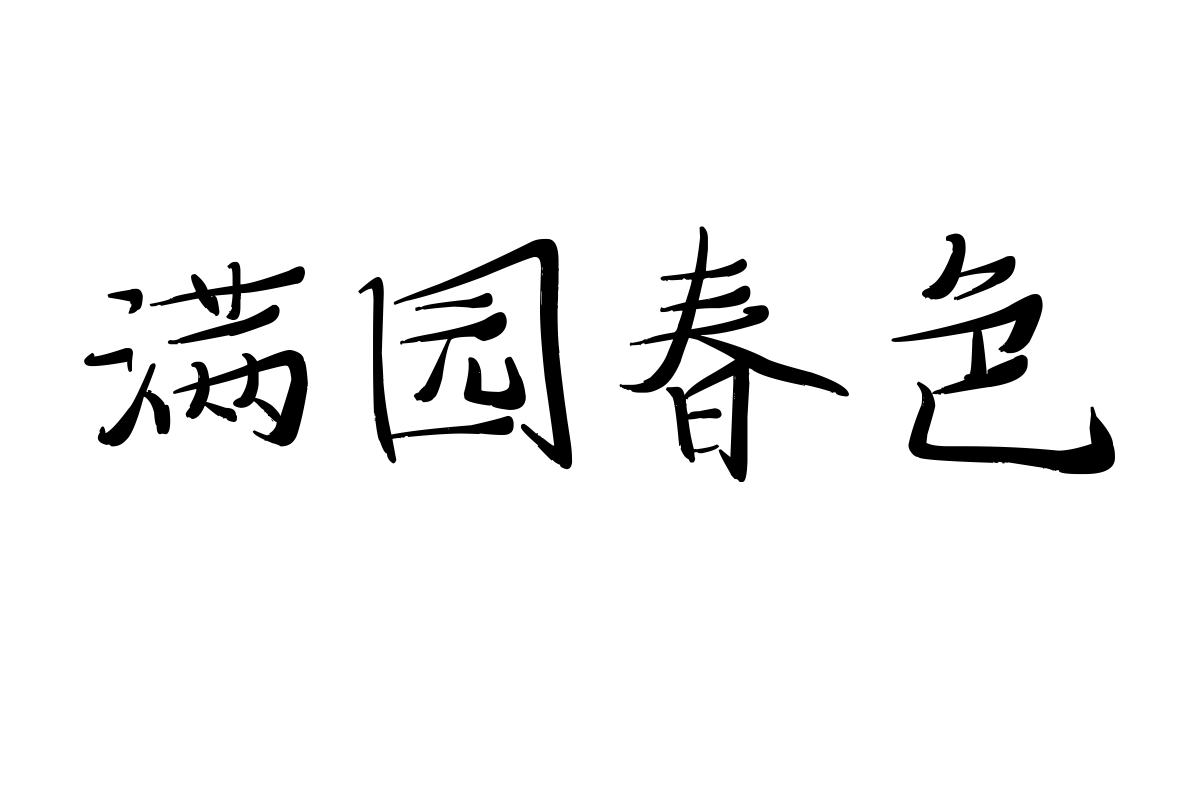
汉仪新蒂美工钢笔是一款专为书写和设计而设计的钢笔,其字体具有独特的美感和实用性。以下是对汉仪新蒂美工钢笔字体的介绍:
1. 设计风格:汉仪新蒂美工钢笔的字体具有现代感和艺术感,线条流畅、简洁大方。它适合用于各种文字设计和书写,无论是标题、正文还是装饰性文字,都能够展现出独特的美感。
2. 字体特点:汉仪新蒂美工钢笔的字体采用了独特的笔画结构,使得文字看起来更加美观和易读。它的笔画粗细适中,既有力度又不失柔和,能够适应不同场景的需求。
3. 应用场景:这款钢笔字体适用于各种文字设计和书写场景,如广告、海报、书籍、杂志等。它不仅能够作为标题使用,还能够作为正文文字或装饰性文字使用,为作品增添一份独特的韵味。
4. 适用人群:汉仪新蒂美工钢笔的字体适合各类人群使用,无论是专业设计师、学生还是业余爱好者,都可以通过这款钢笔字体展现自己的独特品味和创意。
总之,汉仪新蒂美工钢笔的字体以其独特的美感和实用性,为各种文字设计和书写提供了丰富的选择。无论是追求个性还是注重实用性,这款钢笔字体都能满足您的需求。